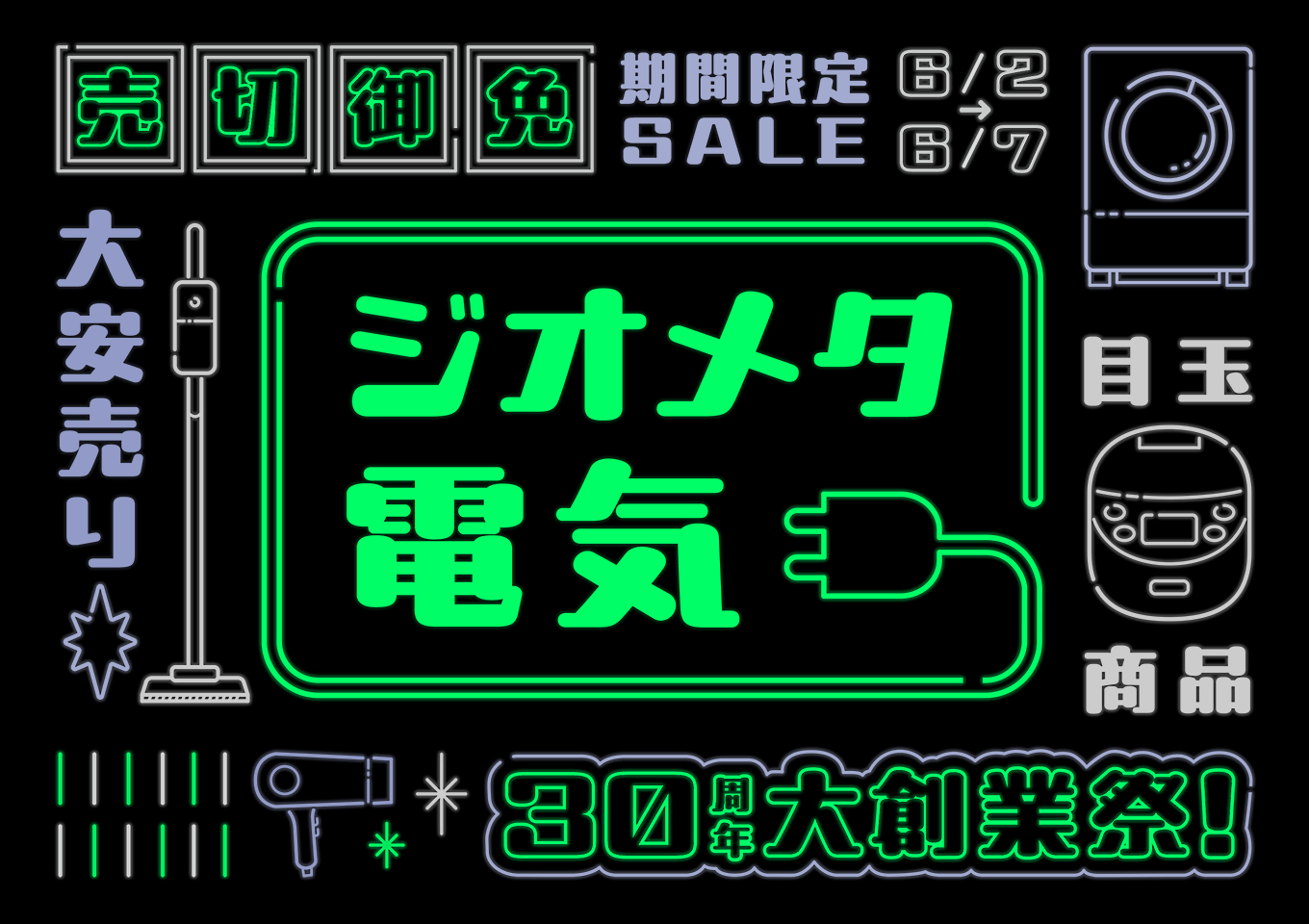
幾何学的な骨格に丸みのあるエレメントを組み合わせたデザイン書体です。水平垂直のラインを意識したやや平体気味のプロポーションやコントラストのある線画が特徴で、インパクトがありながらも親しみやすい表情を演出します。見出し利用に適した太さをもち、広告やコミック、ロゴなど、目を引きたいシーンで活躍する書体です。